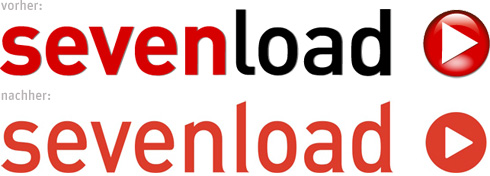
Das Social-Video-Network sevenload.com führt zur TV-Saison 2011 eine rundum erneuertes Corporate Design auf allen Kanälen ein. Anlässlich der in Cannes stattfindenden MIPCOM 2010 präsentiert das Unternehmen seine neue Markenidentität erstmals mit einem eigenen Logo für das TV-Angebot. Im Vergleich zum Vorgänger kommt das neue, einfarbig rote Signet ohne Farbverläufe, Schatten und Glossy-Effekt aus.
Mike Schnoor (Teamleader PR & Corporate Communications) und Markus Dermietzel (Head of Design) schreiben mir dazu per E-Mail: »Als regelmäßige Leser vom Fontblog möchten wir Ihnen heute unser neues Logo vorstellen. … Der Schriftzug im Logo basiert auf modifizierten DIN-Buchstaben. Gleichzeitig setzen wir künftig auf FF Kievit als Hausschrift in unterschiedlichen Schriftschnitten und -größen.« Einem beiliegenden Styleguide konnte ich weitere Details entnehmen. Der DIN-Schriftzug wurde um 87 % horizontal skaliert. Weitere Modifikationen sind angedeutete Fußserifen, schräge Abstriche (außer v), modifiziertes l sowie leicht abgerundete Ecken im Play-Button.
Und weil es in der Mail auch heißt »Wir würden uns sehr freuen, von Ihnen ein konstruktives Feedback zu erhalten«, möchte ich dieses gerne kurz liefern: Besser als vorher, auch ohne die Eingriffe ist DIN eine tolle Schrift; ich persönlich hätte die Manipulationen, wenn überhaupt, auf das gemeine l beschränkt. Viel Erfolg bei der stufenweisen Einführung des neuen Corporate Designs. Ich freue mich auf den ersten Auftritt der (unmodifizierten) FF Kievit.
Eine DIN-Serif wäre doch auch mal ein Projekt für Schriftgestalter.
The interventions in the original DIN make no sense to me. Why add an a-symmetrical serif to n, l, a and d and slice a bit of n, and d AND leave the other glyphs as the were? The minimum requirement (imho) would be to at least cut a slice out of the v and modify (some of) the endings of s, e and a.
And considering the way the round glyphs have been compromised through the ‘squooshing’, my conclusion must be: sloppy job, guys. And nothing to be proud of. (Maybe they didn’t involve a competent type designer?)
Another issue I have is going all red in the revised logo. That can’t be a cost issue, so where did that come from? It weakens the impact of the logo.
As far as I am concerned the best way to ‘improve’ the old logo would have been eliminating the Web 2.0 effects and simplify the Play button.
ein glossy »play« button, es scheint zu funktionieren, ich hab draufgeklickt, was jetzt so toll sein soll an diesem x-beliebigen logo …? man weiß es nicht, aber jetzt kennen auch die fontblog leser sevenload, mission erfüllt.
Autsch. Die DIN modifiziert… Autsch autsch… Das tut schon sehr weh, und lässt das ganze etwas altbacken wirken. Also wenn man keine DIN mehr will, dann sollte man einfach eine andere nehmen anstatt sie zu vergewaltigen. Absolutes “Geht ja mal gar nicht”. Das Zeichen find ich so besser, aber das kann ja auch nichts für die hässliche Modifikation.
Wie modifiziere ich eine Schrift ohne sie zu ändern? Ich schneide ein wenig und klebe ein bißchen, fertig. Irgendwie mußte man wohl den Punkt „Logo-Redesign” unterstreichen. Zum Glück funktioniert die Type trotzdem noch.
Au weia! Da macht sich ein schriftentwerfer viel mühe, eine schrift perfekt zu gestalten und dann gehen ahnungslose kollegen hin und machen sie schlimm. Wenn man serifchen will, kann man sie bestimmt finden und auch schräg abgeschnittene ecken gibt es reichlich. Zu faul zum suchen oder übermotiviert? Es gibt derweil fast 200.000 schriften, das ist gewiss ein albtraum. Aber wenn man ein profil der gewünschten schrift für die logotype erstellt, grenzt man die suche ein. Hier hieße es: bisschen technisch wie DIN; robuste formen, aber schmaler als DIN; leichte serifen, weil feiner; ein paar schrägen, weil dynamischer. Dann merkt man, dass sich diese kriterien widersprechen (technisch./.fein, dynamisch./.robust). Trotzdem wird man eine schrift finden, die auch widersprüchliche eigenschaften ausweist. Notfolglich kann das keine gute schrift sein, weil das hieße, das lächeln der Mona Lisa auf die schultern von Rambo zu verpflanzen.
Gut gemeint ist eben noch lange nicht gut gemacht.
Zunächst: Ich finde die Modifikationen der DIN auch nicht gerade ansehnlich. Ich frage mich, welche Intention dahinter steckt. Einer Schrift Serifen zu verpassen, macht sie ja eher älter, konservativer, traditioneller usw. Im direkten Vergleich der beiden Logos entsteht auch dieser Eindruck. Also was ist die Intention dahinter? Die Attribute einer Serifenschrift passen doch nicht unbedingt zu dem eher frischen, jungen Sevenload-Videoportal… Ich stimme also zu: Bis auf das L hätte man die DIN so lassen können, wie sie ist. Die Serifen sind nichts Halbes und nichts Ganzes, die Schrägen der Oberlängen von L und D irritieren mich.
Davon abgesehen wollte ich aber noch etwas anmerken: Ich finde es lustig, dass hier im Web der 3D-Effekt entfernt wird, während viele Nicht-Web-Unternehmen zunehmend Web-ähnlicher werden. Eine gegenläufige Entwicklung; vielleicht kehrt sich der Prozess bald wieder um.^^
ich komm nicht darauf klar… 87% horizontal skaliert? das ist doch schon konstruktive Kritik! serifen an ne serifenlose schrif? uha. kommt mir vor wie schriftmischung der übelsten art:
“seve” ohne serifen
“nload” mit serifen.
uha.
Also entweder war das vorher eine Extra Wide oder es müsste eventuell
heißen. »Um 87%« heißt für mich, dass jetzt noch 13% übrig sind, und das wäre arg schmal.
Du lieber Gott … was für ein Quatsch diese Modifikation. Rumzerren und dann noch niedliche Serifen anbauen … das kann keiner verstehen. Die Frage ist doch, warum man dann nicht gleich die Kievit auch dafür genommen hat.
ahh, Yetused hat das gleiche geschireben. schließe mich dem einfach mal so an. das rot finde ich ebenfalls zu ausgewaschen.
aber vielleicht bauen sie den rest der webseite ja ebenfalls noch um – ggf. passt das dann alles besser zueinander.
Ich denke das ist ne gute/schlechte PR-Strategie – und wir sind alle drauf reingefallen …